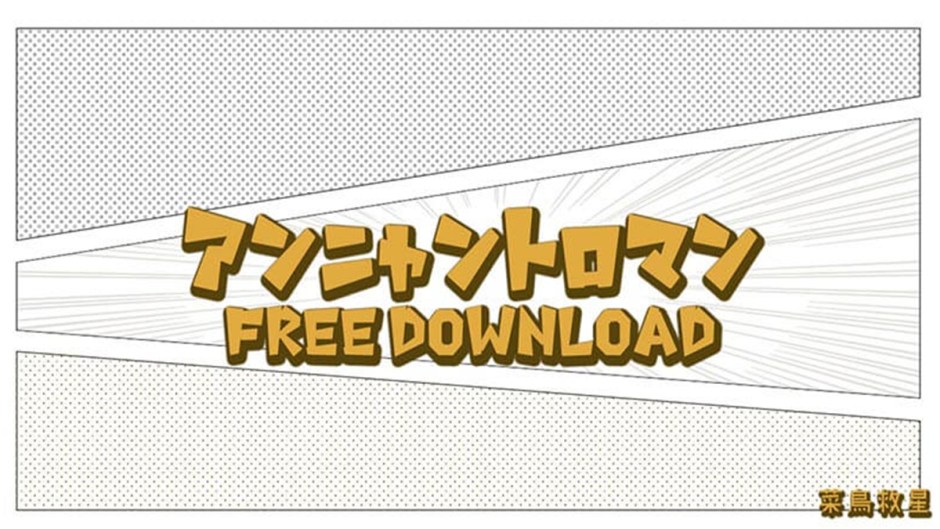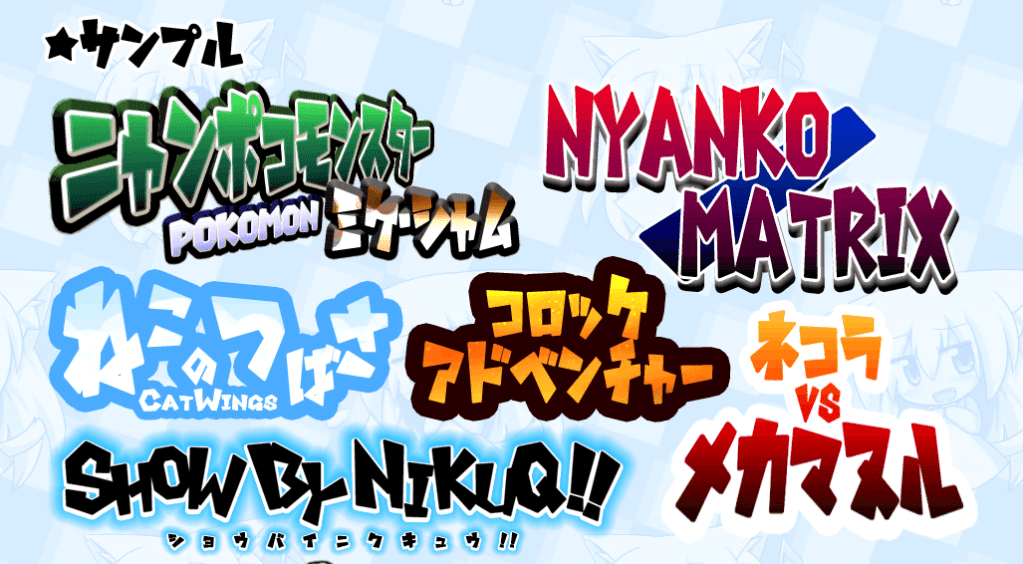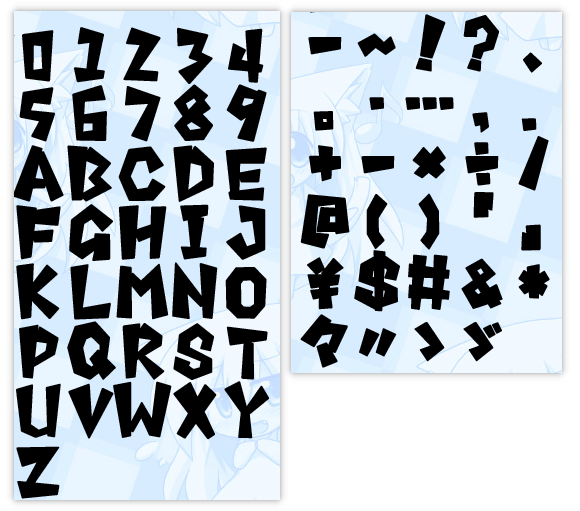
菜鳥救星分享:免費字體下載-アンニャントロマン 發佈日期: 2021-03-022021-03-02 作者: Natty 文、菜鳥編 這次介紹的日文字體,我覺得很有卡漫的味道,雖然沒有支援漢字,但英文部分的使用也可讓你的設計有突顯的效果。喜歡的不妨收藏起來吧。 字體名稱:アンニャントロマン下載位置:http://bit.ly/2GXY0XT 一進到網站,看到的畫面是不是有讓你感受到漫畫冒險的氛圍? 字母、數字及符號的表現如下: 網站下方針對授權部分有很詳細的說明,條件相當的寬鬆,不過禁止偽造作者即將字體應用在商標上。 下方的肉球圖片就是下載位置 下載解壓縮後安裝字體 字體在Adobe與Office中名稱不同: Adobe: Office: 免費字體為網路搜尋而來,使用權限請以官方文件與說明為主 加入菜鳥救星官方Line並回覆「我想看文章」,不定期獲得更多知識吧! 不同頻道,不同知識! Facebook Instagram Youtube 分享此文: 分享到 X(在新視窗中開啟) X 分享到 Facebook(在新視窗中開啟) Facebook 分享到 Telegram(在新視窗中開啟) Telegram 以電子郵件將連結傳送給朋友(在新視窗中開啟) 電子郵件 請按讚:喜歡 正在載入... 相關